无衬线体是西文中没有衬线的字体,它与汉字字体中的黑体相互对应。与衬线字体相反,这一类字体通常是机械形态、线条也是统一的,往往拥有同样的曲率,笔直的线条,锐利的转角。比起衬线体的棱角分明,无衬线较于简洁美观,易于寻找图片上的字体,提升短句美感。
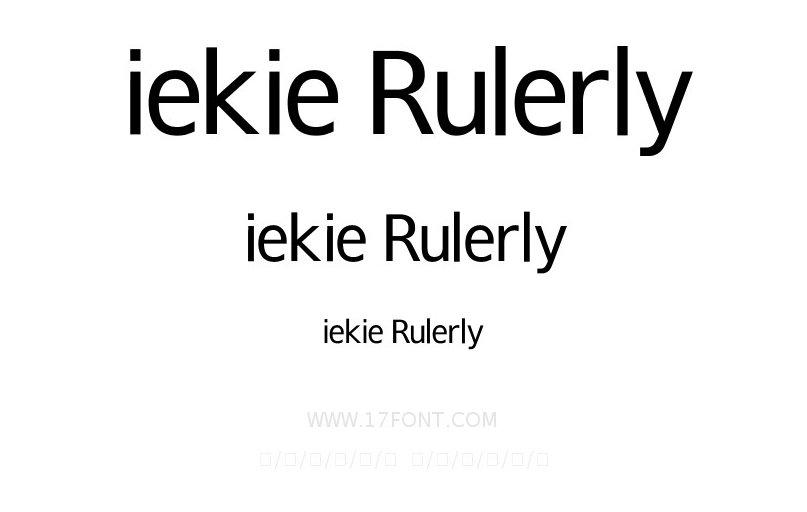
iekie Rulerly:这款字体拥有超高的精确度。线条没有做延伸,没有夸张线型,简洁明了,干净时尚。适用于:游戏、logo设计、广告设计、印刷、屏幕显示、动漫、影视等领域。
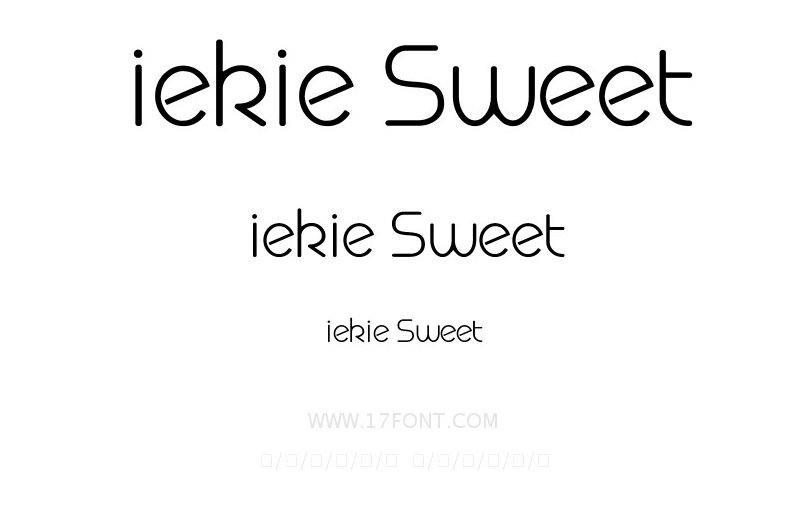
iekie Sweet:这款字体灵感来源于,几乎每个女孩儿童年都离不开的棒棒糖。Sweet这个字体,想表达的出的就是甜蜜的回忆。这款字体用在logo设计、广告设计、印刷、屏幕显示、影视等领域都相当适合。
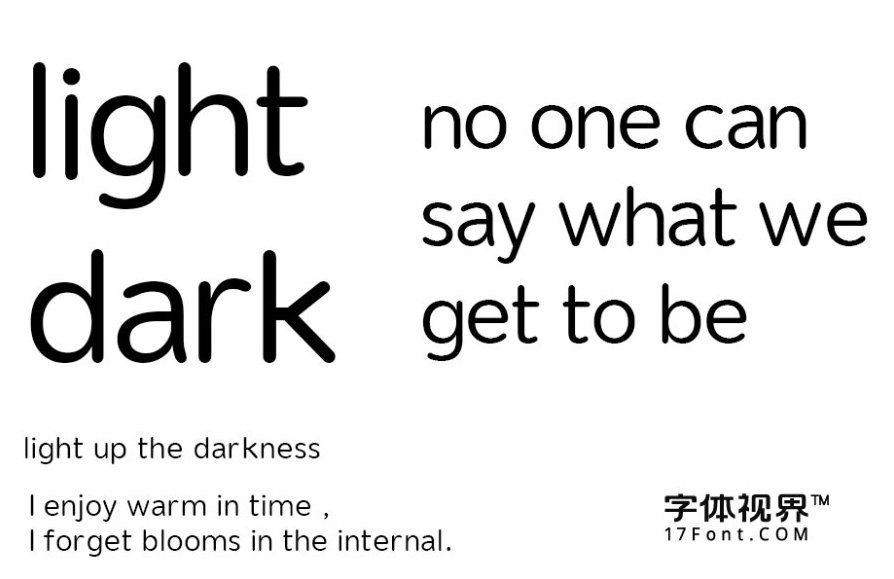
Fabarsolia:这款字体在曲线和对角线的平衡进行了精心调整,为了确保小尺寸的像素和 图片识别字体 都清晰明了。字形圆润整洁,于打印、屏幕显示、内文和标题都非常适用。现在移动设备的时代,扁平化或将成为主流。无衬线字体也逐渐应用在各行各业的设计中,更多无衬线字体,可以在字体视界这个正规商用授权网站上购买下载。